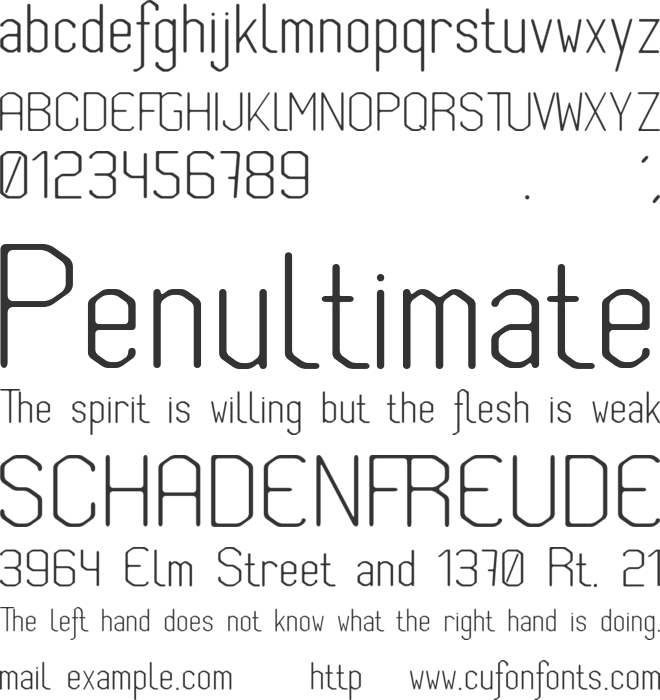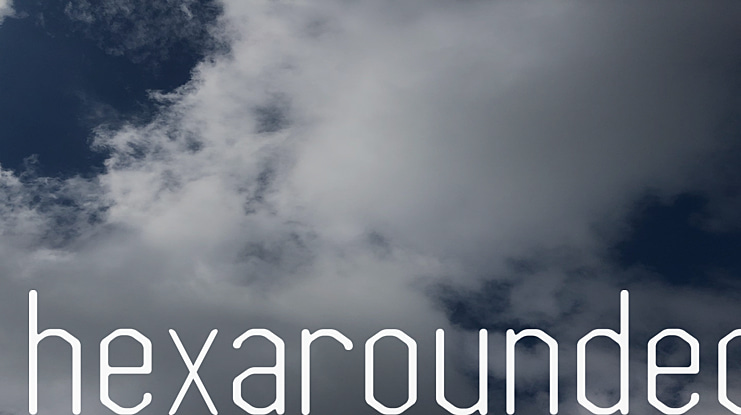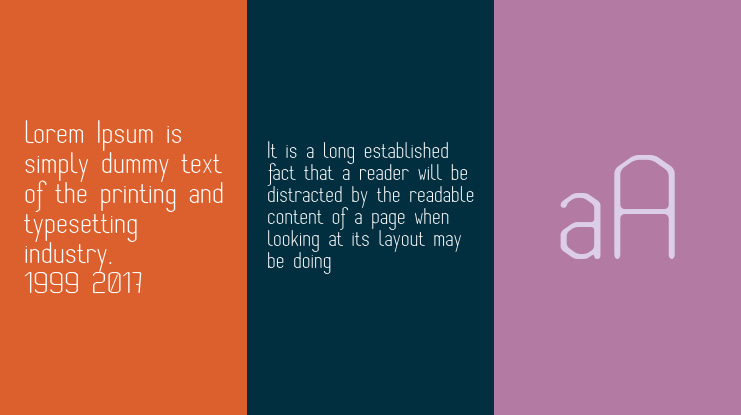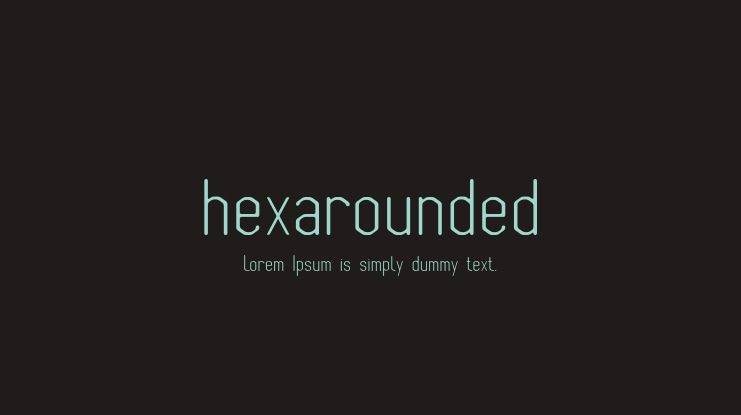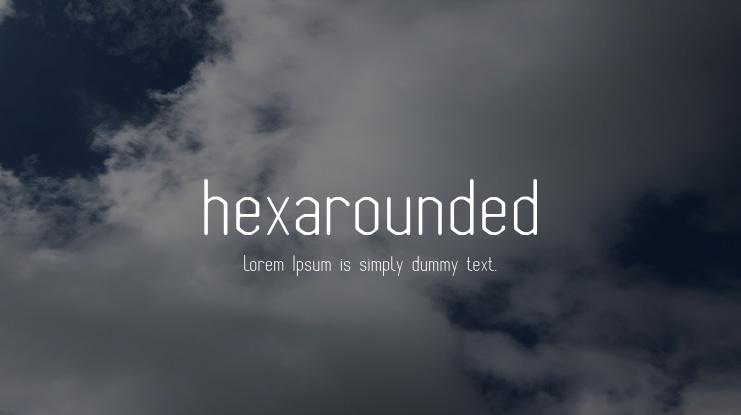
hexarounded Font
Florencio S‡nchez L—pez
La tipografía esta pensada para que sea usada tanto para titulares como para texto corrido.
La hexarounded tiene detalles que la hacen diferente. Diferentes astas para las mayusculas BRP
Ligaduras especiales entre la F, f, l, i e í. Se ha ajustado altura e interletraje de l, i e í con respecto a la caida de las letras F y f. Creando caracteres especiales en Open type.